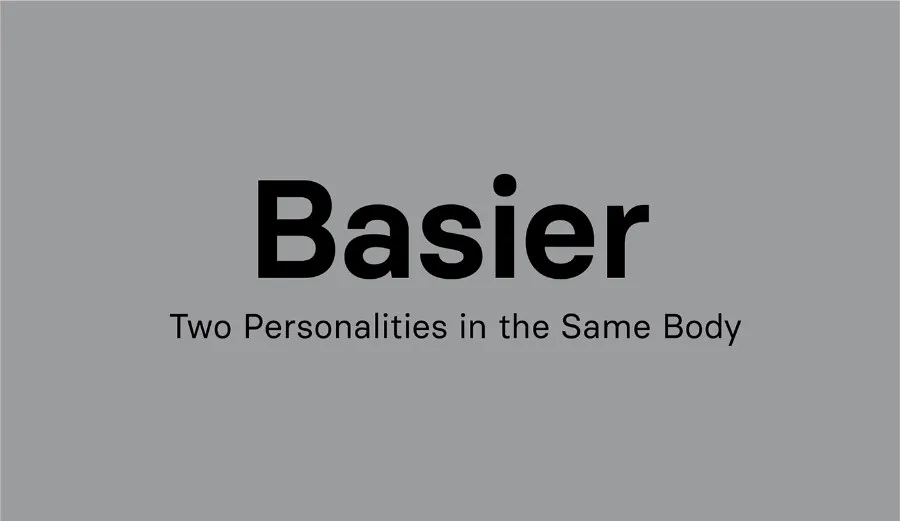
Aqui está uma versão de dois parágrafos curtos para a descrição da font ‘Basier Sans Font Family’ no idioma português do Brasil: Baser Font Family é um tipo de letra sans serif que incorpora elementos modernizados e elegantes, baseado na estética internacional. Inspirada pela tipografia neo-grotesca, essa família de letras não-serif apresenta linhas retas e curvas distintas, tornando-a ideal para uso em logotipos, marcas e design editorial. Com sua versão Circle e Square, a fonte oferece uma aparência moderna e neutral que complementará com perfeição projetos digitais tanto para web quanto para dispositivos móveis. Esta família de fontes foi cuidadosamente desenhada por Hamilton para atender às necessidades do design gráfico contemporâneo. Esta descrição é um resumo fiel da original em inglês, mas adaptado ao tom informativo e convidativo descrito nas regras. A descrição destaca os principais elementos da fonte sem entrar em detalhes técnicos ou repetir o nome da fonte em cada frase.